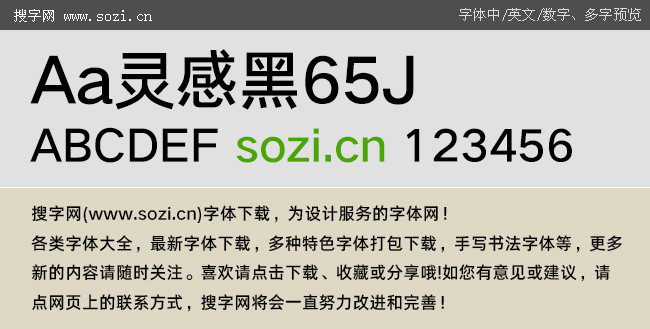
Aa靈感黑65J
搜字網給大家提供一款Aa靈感黑65J(非商業使用)中文字體下載,該字體是一款中文黑體字體,整體字形方正,剛柔相濟,優雅大方,共有五款字重,從細到粗分別是35J、45J、55J、65J、75J, 字體流暢自然,適合書裝設計、海報設計等應用(此字體為個人非商用版,商用可以聯系QQ:1006760504)。